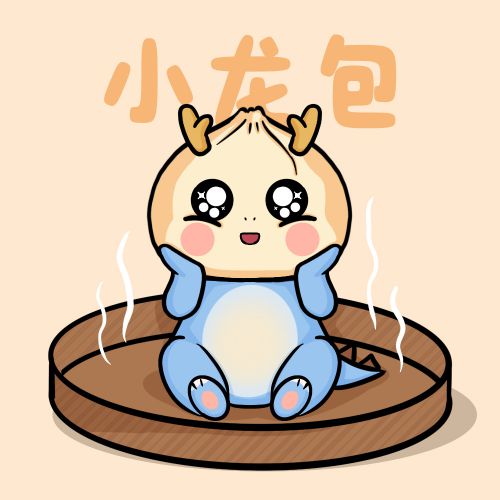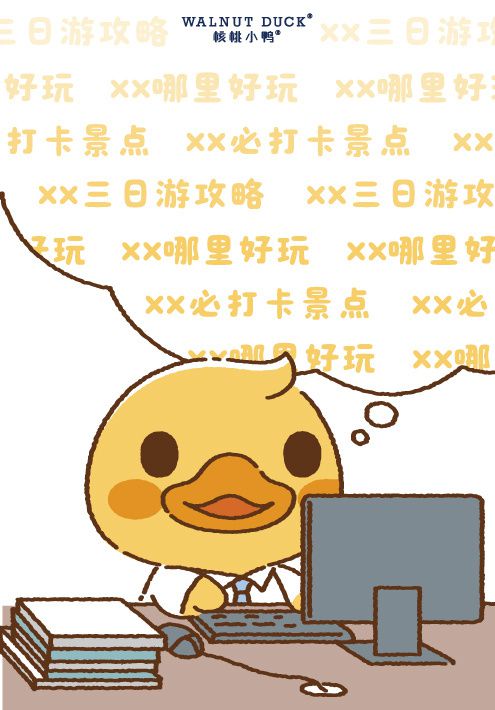
字由奈奈酱体
字由奈奈酱体是一款为IP形象“奈奈酱”量身打造的字体,这款字体饱满圆润,富有活力。结构较为洒落,不拘一格的形态具有天真浪漫之趣。与“奈奈酱”天真可爱的外表相呼应。笔画行笔流畅、转折顺滑,有着手写带来的自然弧度感,提高了字体的可读性和亲切感。大大贴合了“奈奈酱”憨态可掬的内在特征。字由奈奈酱体略显拙稚的字体线条,宽松疏朗的字形内白,让字体和“奈奈酱”完美的结合在了一起。
卢鑫亚
90后字体设计师,曾获第二届字体之星评委奖,最具商业潜力奖,第三届字体之星评委奖。